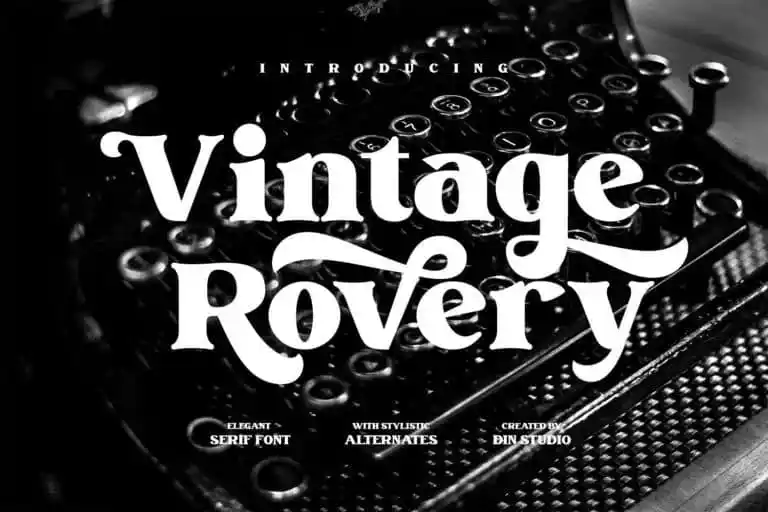
A Vintage Rovery Serif Font é uma escolha moderna para quem busca estilo elegante. Criada pelo Din Studio na categoria de serif fonts, esta fonte oferece alternativas, ligaturas e suporte multilinguístico, garantindo flexibilidade para projetos diversos. Ideal tanto para sua marca online quanto para produtos impressos, esta tipografia traz um toque sofisticado e interessante, tornando-se uma ótima opção para banners do Pinterest, embalagens de produtos ou até mesmo promocionais nas redes sociais. Suas linhas finas e detalhes precisos garantem uma aparência atraente em qualquer plataforma digital ou impressa, tornando-a um recurso gráfico indispensável para projetistas e designers visuais atentos às últimas tendências de design.